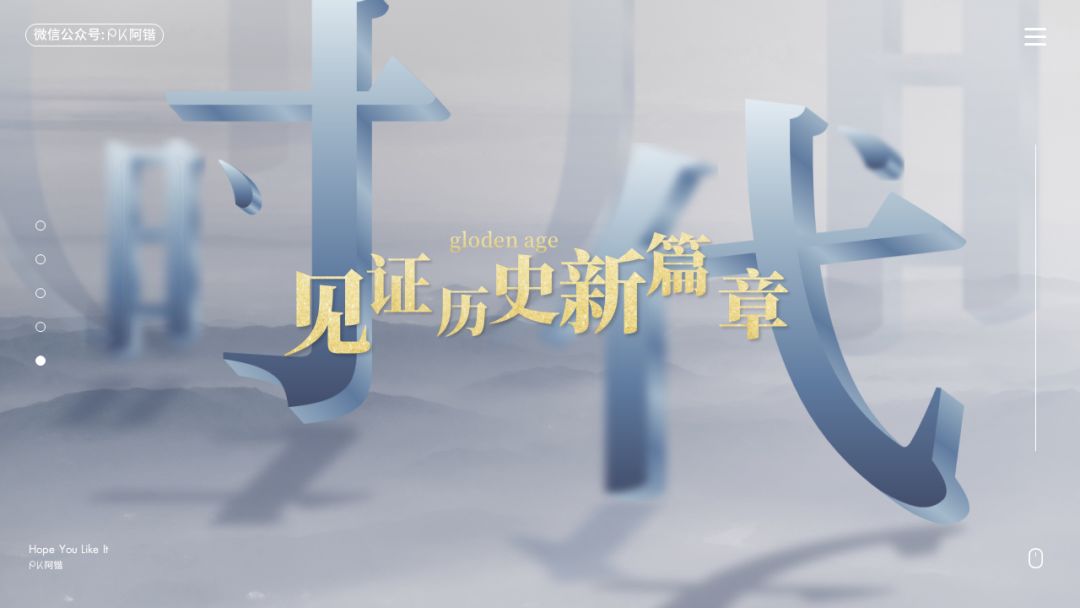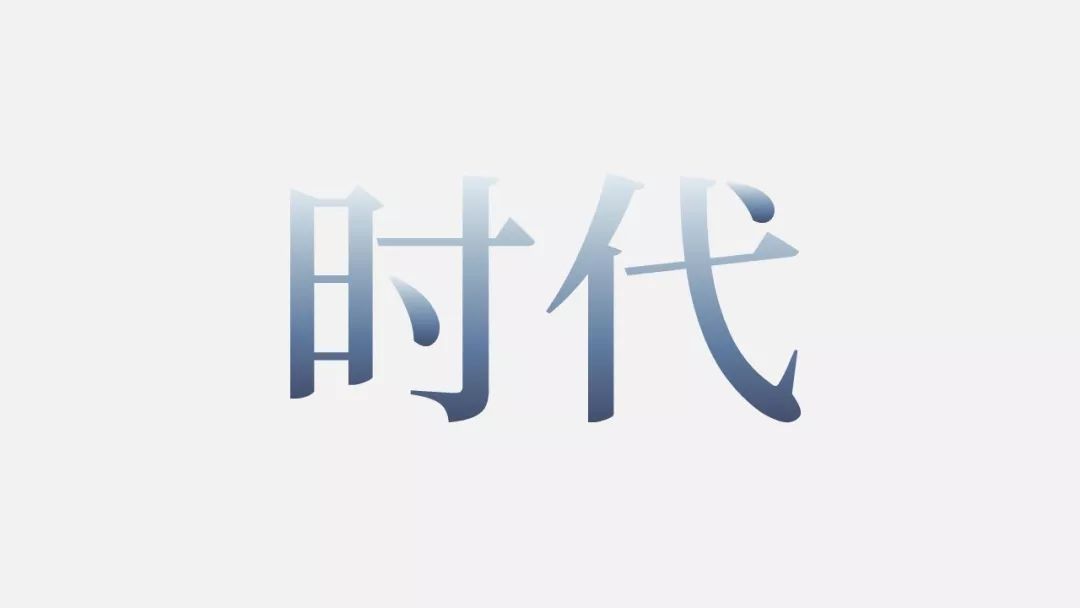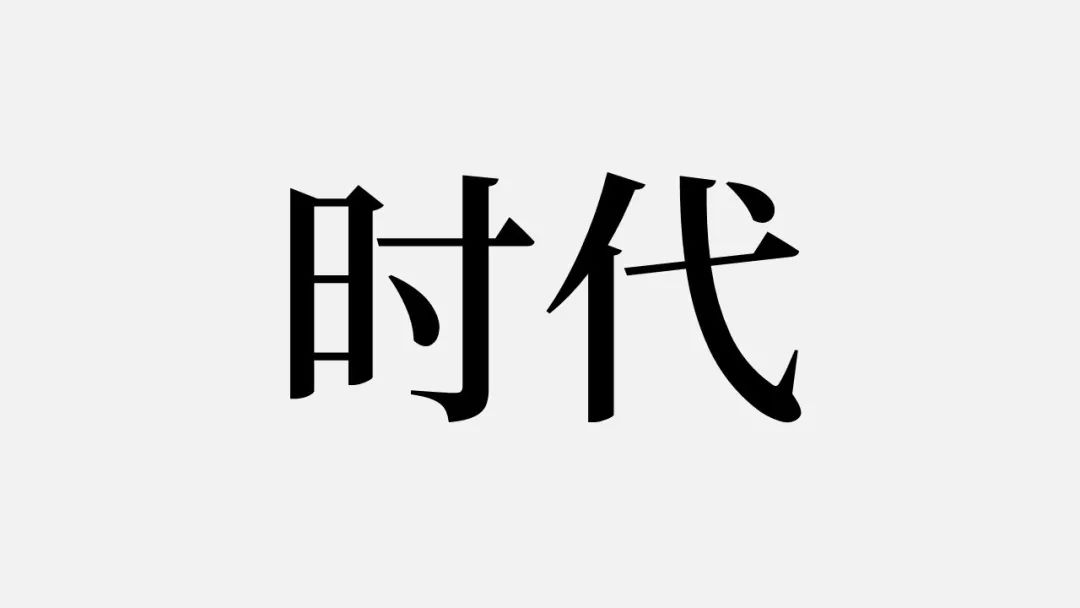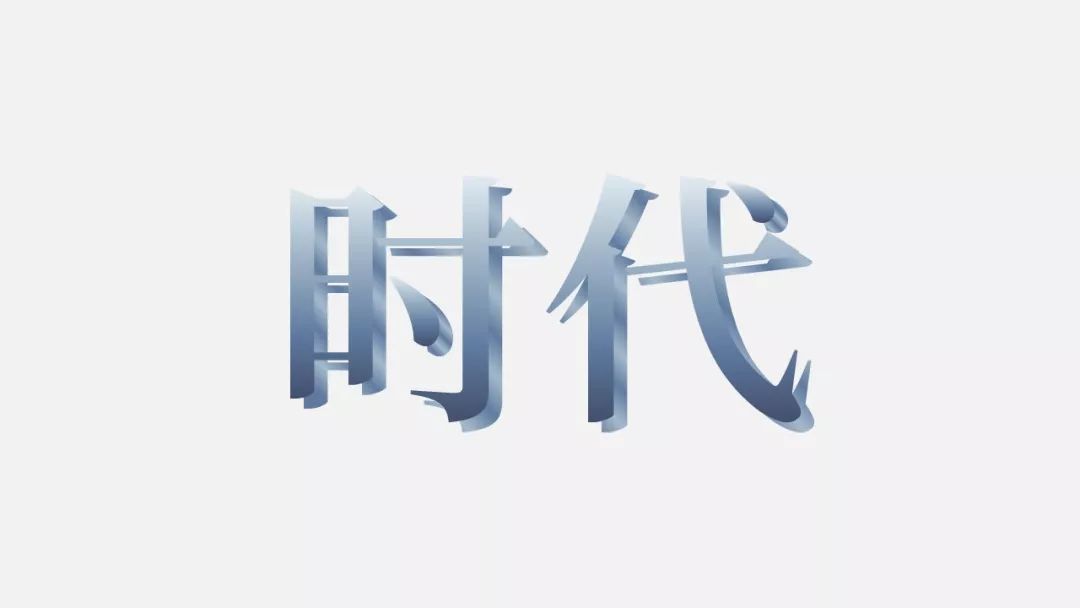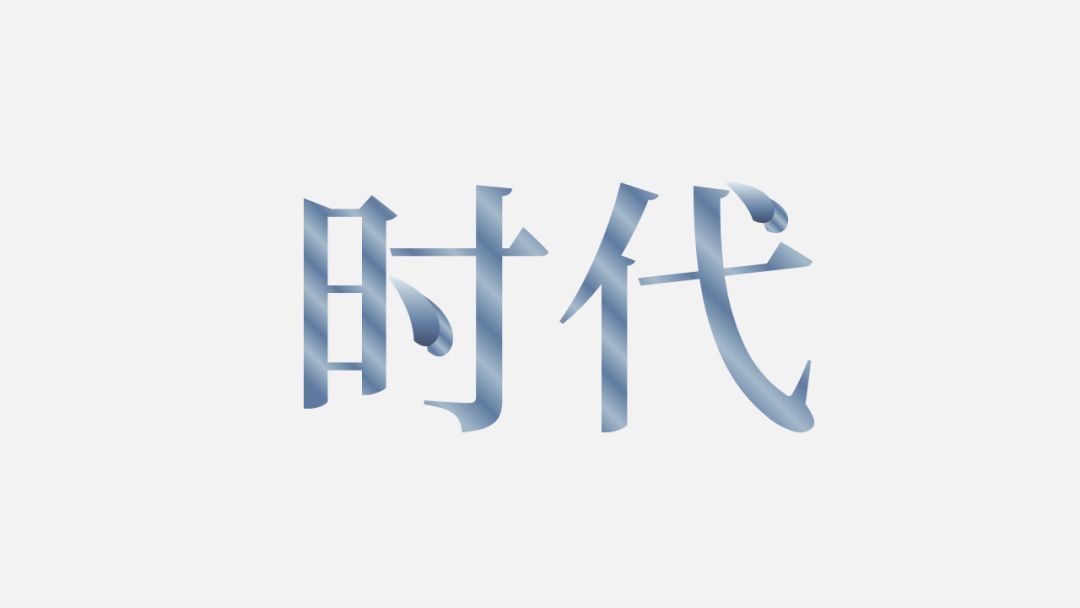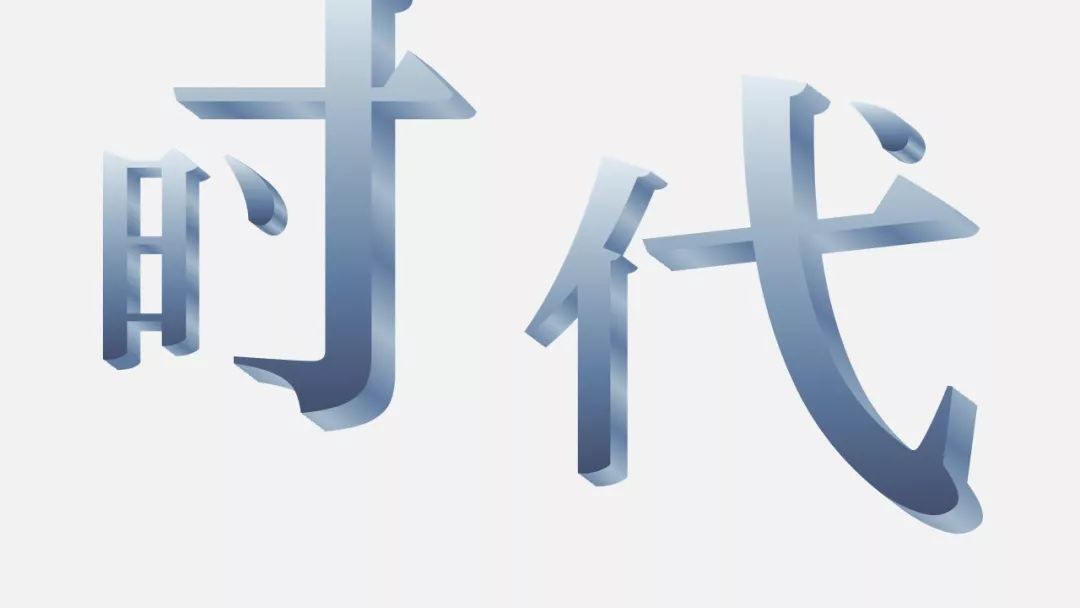
如何用PPT制作电影中的立体字效果?
《PPT保姆级教程》是我新开的栏目,每期挑选一张我制作过的案例,从0到1尽可能详细地,剖析出该幻灯片的设计思路和制作手法,并提供所有相关设计素材,供你练习参考。
动手参与制作,你能得到的,不仅仅是一张超高质量的PPT案例。在练习过程中,你的思维和技法,相信都会大大提升,并且对PPT的功能,也会有更进一步的认识。
NO.2
本期案例:
这页PPT是之前文章所用案例,灵感来源于电影《黄金时代》的海报。
PPT的亮点有三:立体字效果的打造、前后虚实变化、加上阴影所营造的空间感。
以下从5个方面展开讲解制作。
01. 构建主体
首先我们插入文字内容「时代」2字,这里推荐用思源宋体-CN-SemiBold,宋体有衬线,做出来更有感觉。字体大小为240,这个参数不重要,后期可以再调整。
接着,插入一个全屏矩形,同时选中矩形和文字「时代」,依次点击上方功能「格式」-「合并形状」-「拆分」,对文字笔画进行拆分。
可以看到,拆分后字体各笔画都是分开了的。
02.设置渐变,打造立体感
设置渐变,能让笔画看起来更有质感,同时也可以打造出字体立体感。
选中所有笔画,添加渐变,参数如下:
复制一层文字,放在主字体的右下方一些,并放在最底层。
然后对这层新复制的字设置另一种渐变,参数如下:
再把一开始的文字放上去,两者位置如下:
接着我们做字体效果。
选中上下两层里相同的笔画,通过iSlide插件-「补间动画」功能,做出立体质感。这里我设置的参数是15,参数高质感会更细腻,但同时电脑也会卡,这里大家自由调整。
每一个笔画都要「补间」一次,且补间后,各个笔画要分别选中并组合起来,方便后面编辑。
完成后效果如下:
此时我们将某些笔画适当放大,并排版位置,此时可以不用太在意字体的整体的比例。
03.设置虚化-营造虚实感
接着我们给部分笔画做出模糊的效果,营造出远近虚实的感觉。
方法是剪切(复制)笔画,右键—粘贴为图片,依次点击「格式」-「艺术效果」-「虚化」。
设置虚化后,默认的虚化参数是10,觉着不满意的话,可按以下方法调整:
虚化后效果如下:
细心的小伙伴可能会注意到,上边「时」字左边笔画边缘很生硬。所以我们需要将笔画设置边缘虚化,作一个过渡。
设置方法:
案例里我只对3个笔画做了效果,柔滑边缘及虚化参数如下:
04.添加阴影及图片
调整好笔画细节后,我们选中所有的组合,添加阴影,营造空间感。
到这里整体感觉已经7788了,把图片放进去看看效果。
这里我觉得「时代」二字后边有些空了,给它加一些装饰。
创建一个单独页面,复制三个笔画。
这三个笔画装作为装饰,需要压低点透明度,但是PPT中无法直接调节透明度。
怎么办呢?
为了实现这点,我们需要插入一个矩形,与笔画组合框同样大小,并把笔画组合填充到矩形里面,然后就可以调节了,建议透明度参数为90%。
调整透明度后放大大大大大,参考位置如下:
(演示效果需要,这里的设置的透明度是60%)
我们把这三个装饰笔画放到最后面。
这一步做完,整体效果已经完成了。
05.放置文字
最后我们只需要把文字内容放上去就好了。
这里为了文字的阅读效果,我们给它加一层阴影。选中文字后,点击一下「S」的阴影功能就可以了。
最后,找一张金光闪闪的纹理图片,填充文字就OK了。
大功告成,哦森!!
以上就是本期教程的全部内容。用到的功能有三维旋转、补间动画、透视阴影、柔化边缘、调整图片透明度等。